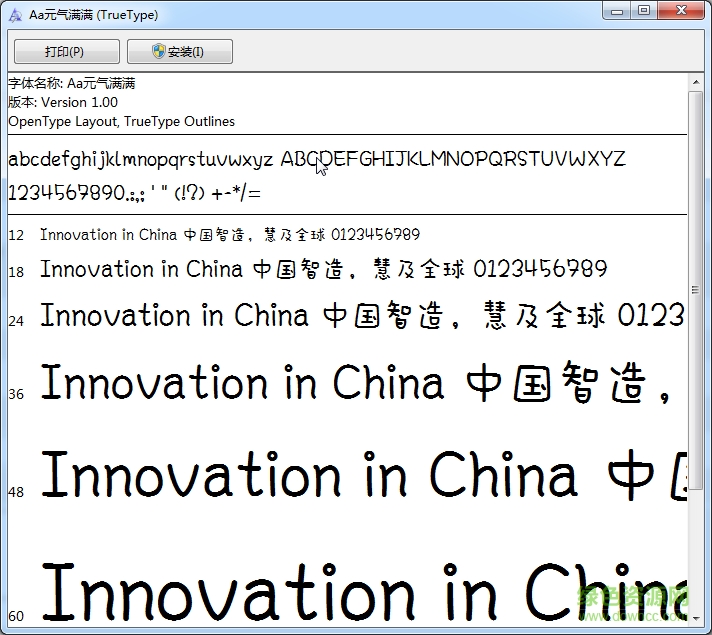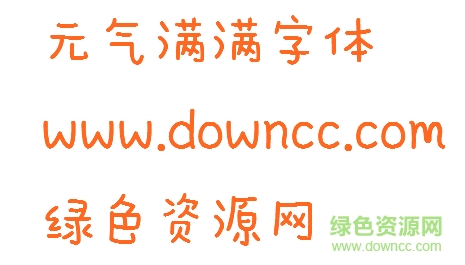
元?dú)鉂M(mǎn)滿(mǎn)字體是一款非?;顫娡娴?a href="http://kiwanis-srv.org/k/katongziti/" target="_blank">卡通字體,如同為你加油打氣般的自信和單純,給你欣喜愉快的好感,來(lái)綠色資源網(wǎng)免費(fèi)嘗試吧!
元?dú)鉂M(mǎn)滿(mǎn)字體風(fēng)格瀟灑大方,流暢自如,整體效果非常的出色,且字庫(kù)完整,非常有手寫(xiě)感,讓人看著會(huì)有元?dú)鉂M(mǎn)滿(mǎn)的感覺(jué),可以廣泛應(yīng)用于廣告設(shè)計(jì)、宣傳海報(bào)、ppt、影視制作以及任何使用文字的領(lǐng)域!
NHK : 元?dú)?(= げんき)…本來(lái)是解作精神…或活力的意思…根據(jù)古籍…“元?dú)狻闭摺褪悄茏屔硇幕顒?dòng)的源動(dòng)力…所以…元?dú)庖部梢砸隇椤】祣…元?dú)鉂M(mǎn)滿(mǎn)…就是指精神飽滿(mǎn)…或是活力十足…或是人很健康的意思……